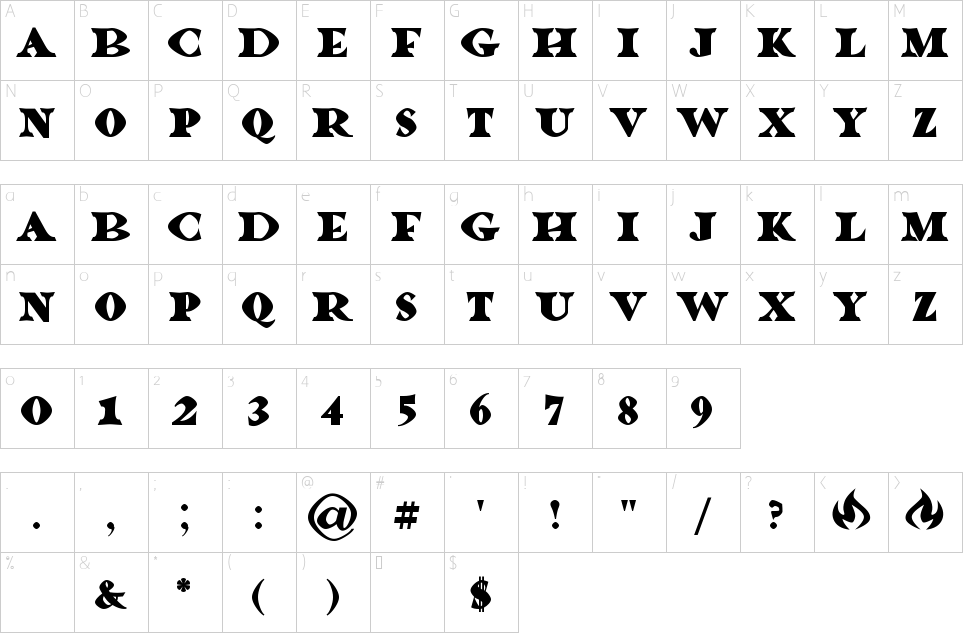
Dragonlands Font
A Dragonlands Font é uma criação inovadora que você certamente vai adorar para suas próximas projetos digitais. Desenvolvida por Darrell Flood, esta elegante e sofisticada fonte oferece um aspecto vibrante e único que não poderia ser encontrado em outras opções disponíveis no mercado de fontes gratuitas. Download Dragonlands Font agora para Windows e Mac e descubra o poder desta ferramenta visual. Com sua arquitetura única, a Dragonlands Font é perfeita para aqueles que buscam um estilo único e moderno. Seja você um designer gráfico profissional ou um criador de conteúdo em desenvolvimento pessoal, essa fonte irá trazer uma nova dimensão aos seus projetos digitais. A cada dia mais pessoas descobrem o valor dessa fonte com downloads superiores a 5 mil, e agora é sua vez de se juntar à comunidade que ama Dragonlands Font.
Mapa de caracteres da fonte Dragonlands Font